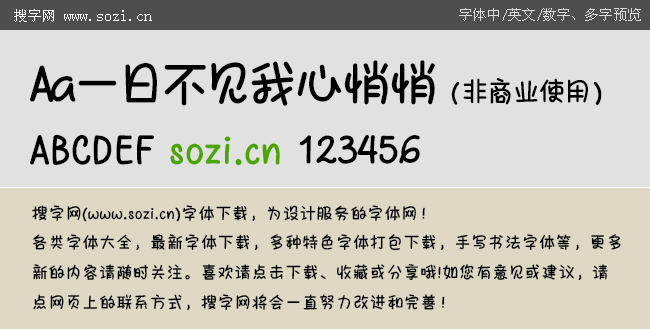
Aa一日不見(jiàn)我心悄悄
搜字網(wǎng)給大家提供一款A(yù)a一日不見(jiàn)我心悄悄(非商業(yè)使用)中文字體下載,Aa一日不見(jiàn)我心悄悄是一款手寫(xiě)的卡通風(fēng)格字體,字形可愛(ài)俏皮,透出一些稚氣。書(shū)寫(xiě)上融入了連筆,活潑靈動(dòng)。適合應(yīng)用于藝術(shù)設(shè)計(jì)、平面宣傳設(shè)計(jì)、網(wǎng)頁(yè)設(shè)計(jì)、海報(bào)設(shè)計(jì)等應(yīng)用(此字體為個(gè)人非商用版,商用可以聯(lián)系QQ:1006760504)。